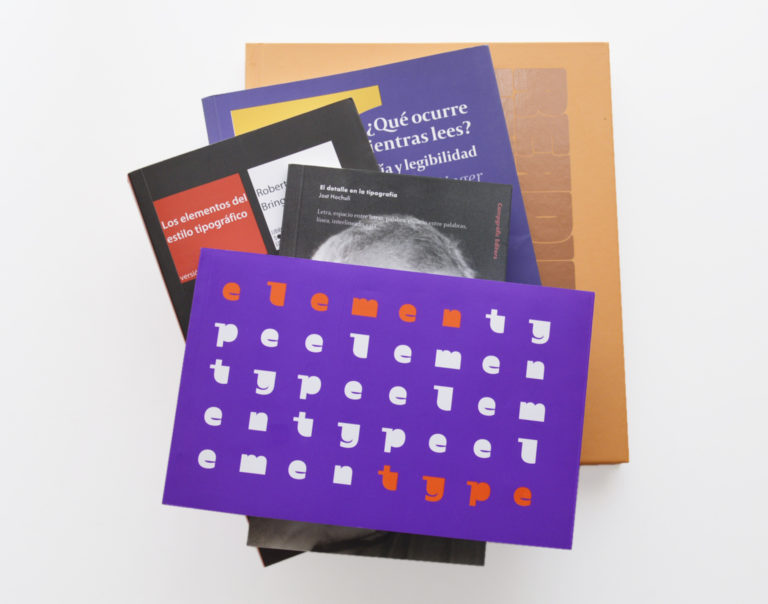
Cinco libros sobre tipografía, sobre cómo usarla correctamente, es decir, cómo comprenderla profundamente, cómo adentrarse en la esencia simbólica y conceptual de las letras en tanto que formas (pero mucho más). Estos cinco volúmenes son muy diferentes entre sí y, por lo tanto, complementarios. Cada uno de ellos nos aporta una visión particular, una perspectiva distinta y original desde la cual otear un paisaje tan abigarrado y seductor como el de la tipografía. Entrad sin llamar.
Los elementos del estilo tipográfico
Este libro fue el primero que me recomendaron cuando decidí adentrarme en los entresijos del mundo tipográfico y también es el primero que recomiendo cuando me preguntan qué leer para aprender más sobre tipografía. «La tipografía es el arte de dotar al lenguaje de una forma visual duradera». Esta afirmación de Robert Bringhurst, digna de grabarse en piedra, como muchas otras a lo largo y ancho de la obra, suele estar en el inicio de muchas de mis clases y conferencias. Bringhurst, también poeta, es un sabio que escribe divinamente bien, y el modo en que nos hace adentrarnos en el origen y la historia de la tipografía, sus reflexiones sobre el ritmo, la armonía y la proporción tipográfica o las composiciones de páginas, bajo el prisma del tipógrafo, pero también del literato, resultan envolventes, sugestivas y muy bellas.
- Título: Los elementos del estilo tipográfico
- Autor: Robert Bringhurst
Reading letters. Designing for legibility
La finalidad de la mayoría de los trabajos tipográficos es una recepción óptima del texto. La cuestión de lo formal es de facto una cuestión de legibilidad. Reading Letters, ofrece conocimientos tipográficos relacionados con la legibilidad de gran implicación en el diseño. Basado en estudios con base científica, se complementa con ejemplos visuales de legibilidad. Aborda temas tan interesantes como las proporciones de los caracteres en la distancia y su relación con los nuevos sistemas de señalización o la importancia de entender las diferencias de las nuevas demandas en lo que a soporte se refiere y que necesitan de tipografías contemporáneas que cumplan con estas necesidades. Imprescindible para todos aquellos profesionales cuya materia prima sean las letras.
Reading Letters está escrito por Sofie Beier, diseñadora, investigadora y profesora en The Danish Design School, dirige, además el Centre for Visibility Design, donde se estudia sobre soluciones que puedan ayudar a optimizar situaciones de legibilidad difíciles basándose en la combinación de métodos de la psicofísica con la investigación por diseño. Su leitmotiv es crear un diseño universal que pueda mejorar la vida diaria de todos.
- Título: Reading Letters. Designing for Legibility
- Autor: Sofie Beier
¿Qué ocurre mientras lees? Tipografía y legibilidad
¿Alguna vez te has preguntado cómo se lee? ¿Qué posibilidades existen para ofrecer mejores letras y tipografías a los lectores? ¿Cómo reaccionan la vista y el cerebro al leer? Respuestas, reflexiones y conocimiento, mucho conocimiento, se encuentran en esta obra imprescindible que acerca al lector al proceso que se produce cuando realizamos algo tan aparentemente común y cotidiano como leer.
Patrones de lectura, hábitos de lectura, las formas de las letras, convenciones, y explicaciones necesarias para comprender lo que ocurre en el momento de la lectura. Escrito por Gerard Unger, el que fuera mentor de multitud de diseñadores de tipografías actuales, un verdadero maestro del diseño tipográfico, nos ha legado un compendio de sabiduría tipográfica sin límites.
- Título: ¿Qué ocurre mientras lees? Tipografía y legibilidad
- Autor: Gerard Unger
Elementype. Una guía práctica del uso tipográfico
Tipastype tienen claro que «la tipografía no debería ser un terreno complicado para su entendimiento y uso práctico». Fruto de esta creencia y de mucho trabajo es la edición de su primer libro, Elementype, en colaboración con Mónica Munguía, una obra de consulta rápida y contundente que facilita el aprendizaje de conceptos tipográficos, básicos y complejos, a través de numerosos ejemplos, gráficas y textos claros y directos.
Tipastype son Dafne Martínez y Sandra García, componentes de la primera fundición tipográfica latinoamericana formada íntegramente por mujeres. Afrontan la tipografía desde todos los ángulos posibles, no solo desde del diseño y la producción, sino también desde la vertiente educativa. Rezuman entusiasmo y energía y son un ejemplo para la comunidad tipográfica.
Ficha técnica
- Título: Elementype. Una Guía Práctica del Uso Tipográfico
- Autor: Dafne Martínez, Sandra García y Mónica Munguía
- Editorial: Autoeditado
- Idioma: Español
- Páginas: 120
Fotografías: Ana Moliz
El detalle en la tipografía
¿Sabes cómo funciona el proceso de lectura en un lector experimentado? ¿Sabes que el ojo no capta los caracteres uno por uno sino que percibe formas de palabras enteras o que la línea es la tercera unidad de la microtipografía? Estas y otras muchas cuestiones más sobre la importancia de la tipografía, tanto en comprensión de textos como en legibilidad, se encuentran en El detalle en la tipografía de la fabulosa editorial Campgràfic, obra breve pero intensa de Jost Hochuli, autor del que ya hemos hablado en anteriores ocasiones con motivo de otro de sus grandes obras, El diseño de libros.
Para que los textos sean leídos y la lectura no canse es preciso que todos los detalles que conciernen a caracteres, líneas, párrafos, espaciado y blancos estén en su justo lugar. Un muy recomendable libro, clarificador y fácil de leer.
- Título: El detalle en la tipografía
- Autor: Jost Hochuli